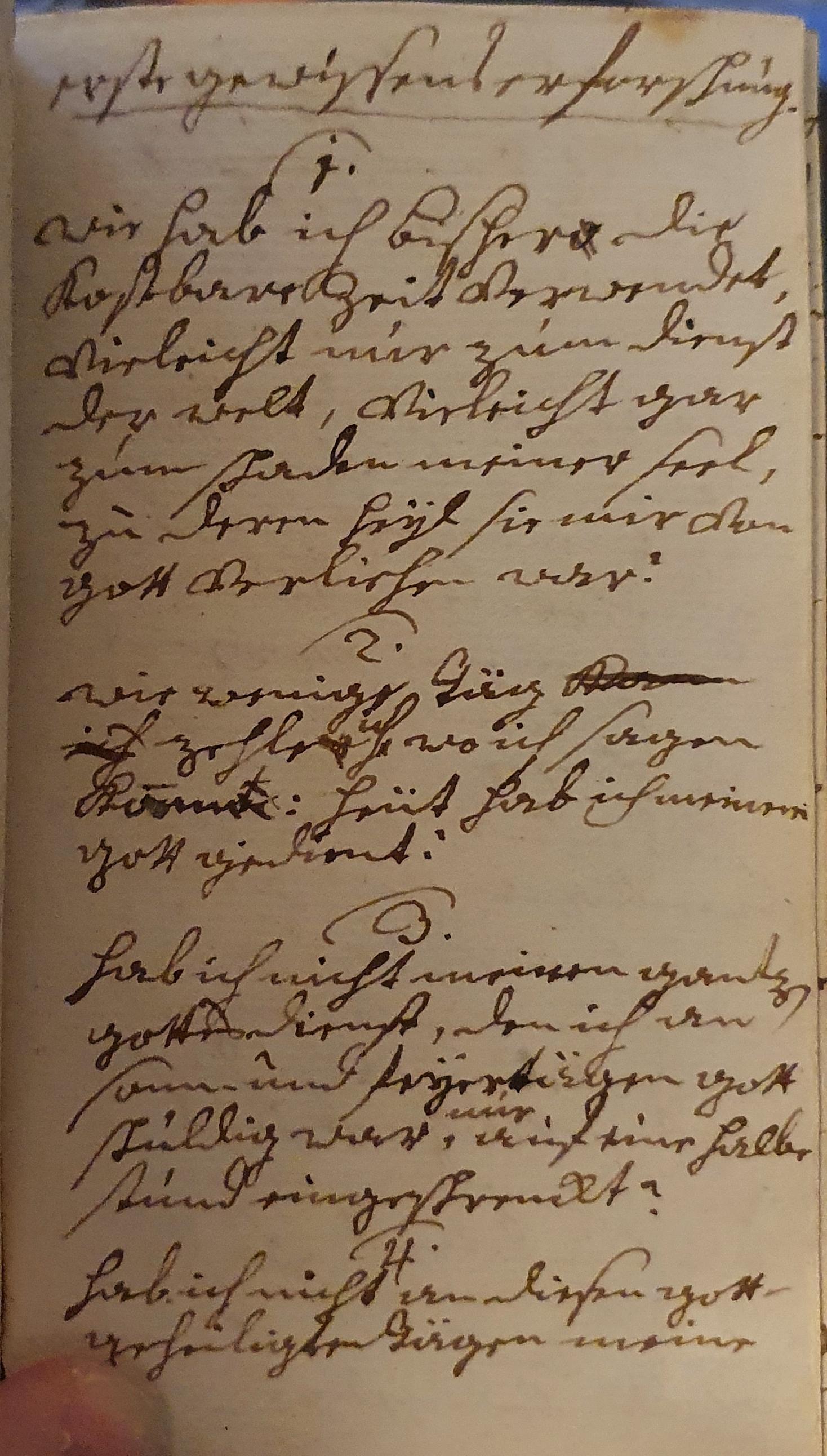
Gebettext aus dem 18. / 19. Jahrhundert
vor ein paar Tagen habe ich mir ein kleines Buch von 1774 in einem Antiquariat bestellt. Das Buch hat keinen direkten Titel. Die Überschrift auf der ersten Buchseite lautet: "Das Seelen-Geschäft". In das Buch wurden handschriftlich ein paar Gebete geschrieben. Eine Seite dieser Gebettexte habe ich abfotografiert und hier angefügt. Könnt ihr mir bitte ein Stück von dieser Seite entziffern, gerne auch die erste unterstrichene Zeile? Was mich darüber hinaus interessiert: Kann man aus der Handschrift ein Stück weit ableiten, ob das Gebet ungefähr im Zeitraum der Buchausausgabe, also Ende des 18. / Anfang des 19. Jahrhunderts in das Buch eingetragen wurde?
1.
wie hab ich bisher die kostbare Zeit verwendet, vieleicht nur zum dienst der welt, vieleicht gar zum schaden meiner seel, zu deren heÿl sie mir von Gott verliehen war?
2.
wie wenige Täg zehle ich, wo ich sagen kann: heüt hab ich meinem Gott gedient?
3.
hab ich nicht meinen gantzen Gottesdienst, den ich an sonn und feÿertägen Gott schuldig war, nur auf eine halbe stund eingeschrenkt?
Zur zeitlichen Einordnung: Ich bin kein Experte in diesen Dingen. Aber aufgrund der Orthografie und des Schriftstils würde ich es eher früher als später einordnen; Ende 18. Jh. scheint mir plausibel.
"Aber aufgrund der Orthografie und des Schriftstils würde ich es eher früher als später einordnen; Ende 18. Jh. scheint mir plausibel.", das finde ich interessant. Kannst du mir bitte Beispiele dafür nennen?
Meine Erfahrungen mit Kurrentschrift sind sehr punktuell: Predigten und amtliche Dokumente ungefähr aus der Zeit um 1760 und dann ein Briefwechsel, der ungefähr die Zeit von 1850 bis 1890 abdeckt (plus weitere Dokumente aus dem Umkreis der Briefschreiber). Wenn ich mir Rechtschreibung und Stil dieser Dokumente in Erinnerung rufe, liegt Dein Beispiel deutlich näher an 1760 als an 1850. Das ist aber natürlich alles mit Vorsicht zu genießen, weil es große Unterschiede zwischen einzelnen Schreibern, Regionen, Arten von Dokumenten etc. gibt. Du könntest für den Anfang nach Netzseiten Ausschau halten, wo man Kurrentschrift erlernen kann; zumeist gibt es dort eine Reihe von Übungstexten aus verschiedenen Zeiten (samt Transkription), anhand deren man die Unterschiede gut sehen kann.
Danke für deine Rückmeldung. Das "Wenn ich mir Rechtschreibung und Stil dieser Dokumente in Erinnerung rufe, liegt Dein Beispiel deutlich näher an 1760 als an 1850." kommt gut hin, da das Buch 1774 erschienen ist.